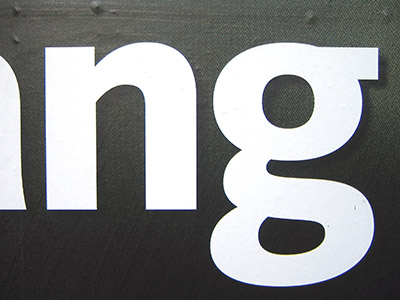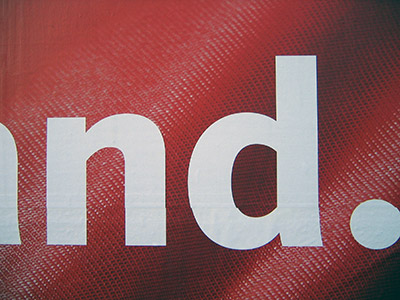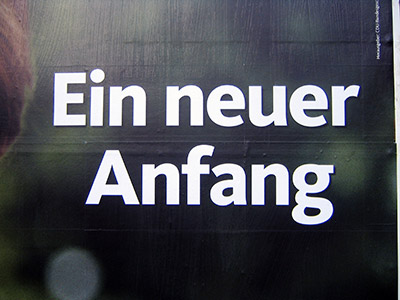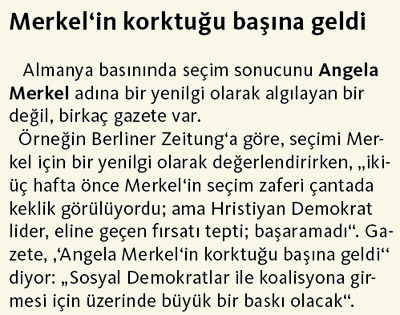
Siegerin der Typo-HerzenVerlierer gebärden sich als Sieger, Gewinner stehen im Abseits –
verrückte Wahl 2005. Der wahre Champion ist eine junge Schrift namens
Kievit. Sie hinterließ auf den Plakaten der CDU einen bleibenden
Eindruck. FontShop weiß sogar, dass die CDU-Bundesgeschäftsstelle
längst eine türkische Version der Kievit in der Schublade hat.
Also doch mehr als eine privilegierte Partnerschaft? Weiterlesen ...
![]() Die Familie FF Kievit ist ein Jungtalent unter den
Schriften. Der US-Designer Mike Abbink begann bereits an der Hochschule mit der
Arbeit an Kievit (1995), die er 2001 beendete. Zum ersten mal kamen
einige Schnitte der Schrift 1999 zum Einsatz im Corporate Design des
New-Economy-Unternehmens »Personify«.
Mike Abbinks Designmission lautet schlicht Lesbarkeit. Um dies zu erreichen, suchte er nach einem Kompromiss zwischen klassischer Buchstabenform und konstruierten Zeichen. Ein Bild aus der Anatomie fasst das Kievit-Geheimnis anschaulich zusammen: Grotesk-Fleisch auf Antiqua-Knochen. Das innere Bauprinzip der Kievit-Buchstaben basiert auf den bewährten Qualitäten klassischer Serifenschriften: große Mittellänge (x-Höhe), Kleinbuchstaben mit Oberlängen (außer t) überragen die Versalien, Antiqua-g, Mediävalziffern, ausreichend Kontrast in der Strichstärke. Ihre Konturen müssen sich mit großen humanistischen Vorbildern wie Frutiger oder Syntax messen lassen, die jedoch von der Konstruktion her geometrischer angelegt sind. ![]() Geradezu mustergültig erfüllte die CDU-Schrift Kievit im Wahlkampf ihre Aufgaben: sie war bestens lesbar, stets wiedererkennbar und solide in großen wie auch kleinen Auftritten (Foto: Fontblog). Vielleicht das auffälligste Merkmal der Kievit sind die großen runden Punkte bei Buchstaben und Satzzeichen. Ein nicht unbedeutendes Merkmal für eine Schrift, die in Deutschland, der Heimat der Umlaute, ihren Dienst tun soll. Ihre Wirkung für die Lesbarkeit tritt vor allem bei klein gesetzten Texten in Erscheinung. In den Riesen-Slogans der CDU leisteten sie ihren Beitrag zur Unverwechselbarkeit. ![]() Geschliffen stand der Slogan »Ein neuer Anfang.« auf dem Großflächenplakat, optisch aufpoliert durch einen leichten Schatten nach rechts unten. Das Antiqua-g ist ein außergewöhnliches Merkmal der Kievit (Foto: Fontblog). Seit Anfang 2004 setzt die CDU die beiden Strichstärken Book und Bold der Kievit-Familie ein. Sie sind essenzieller Bestandteil des neuen Corporate Designs, mit dem sich die Partei ein bundesweit einheitliches Erscheinungsbild geben will (siehe: Corporate-Identity-Portal der CDU). Bis dahin verwendete die Bundeszentrale eine Franklin Gothic, während in den Verbänden unterschiedliche Schriftarten zum Einsatz kamen. Eine gemeinsame, bundesweite Schrift wurde die Basis für optische Geschlossenheit. ![]() Überdurchschnittlich große, runde Punkte in Buchstaben und Satzzeichen sind ein auffälliges Merkmal der Kievit (Foto: Fontblog). Mehr zur Entstehung der FF Kievit (die in Deutschland exklusiv von FontShop vertrieben wird) ist auf den folgenden Seiten nachzulesen: Typografie-Fanseite daidala.com von Jon Colz: Interview mit dem Schriftentwerfer Mike Abbink, Schriftmuster Online-Design-Magazin Reservocation: Interview mit Mike Abbink plus Abbildungen Type Directors Club Designwettbewerb 2001: eine der Gewinnerschriften ist FF Kievit FontShops Corporate Font Abteilung hat die Bundes-CDU bei der Einführung ihrer neuen Hausschrift begleitet. Zum Beispiel mit der Entwicklung einer bildschirmoptimierten TrueType-Version und einer Sprachversion für die türkische Sprache. Hoppla ... Türkisch? Lässt die Schriftausstattung der CDU möglicherweise den Schluss zu, dass die distanzierte Politik gegenüber der Türkei vielleicht gar nicht so eisern gemeint ist, wie Unionspolitiker ständig betonen? Hoffen wir das Beste. ![]() Die Türkische Version der CDU-Schrift Kievit liegt schlüsselfertig auf den Rechnern der Bundeszentrale (Schriftmuster: Fontblog) Herausgegeben: Mo - September 19, 2005 at 10:29 vorm. | |